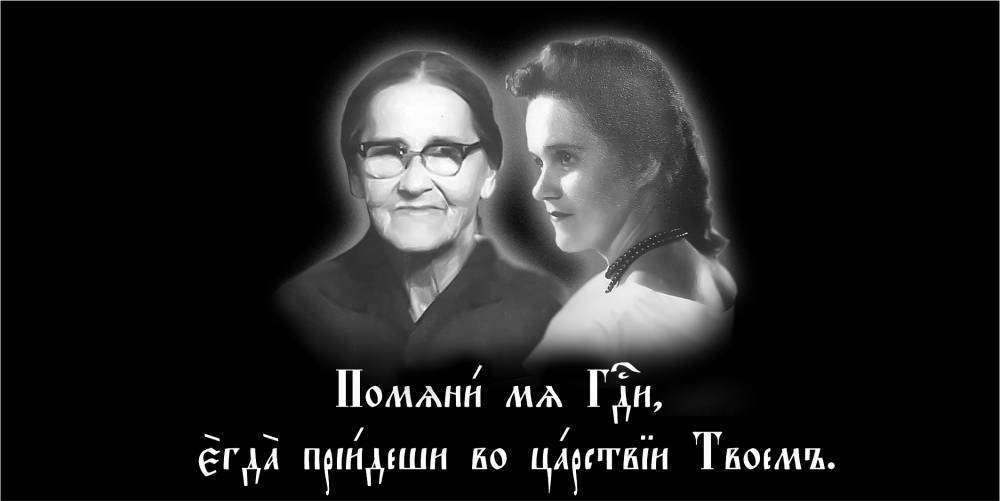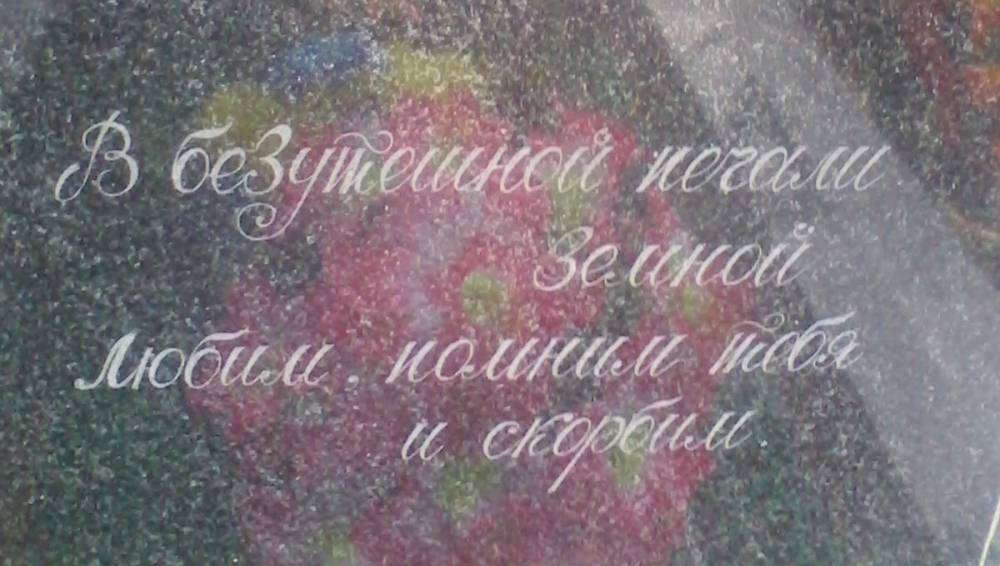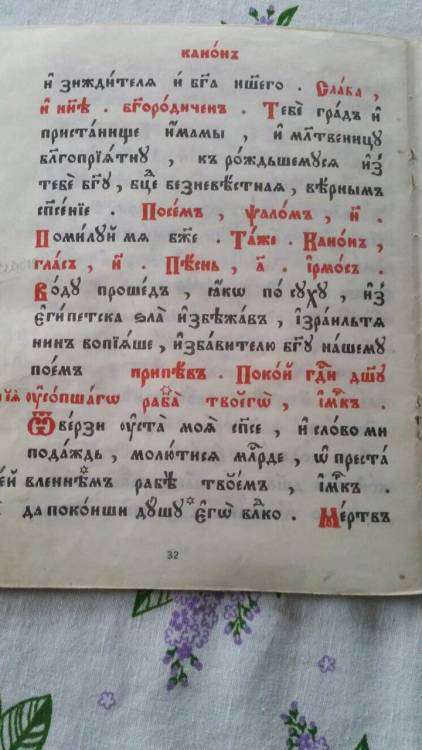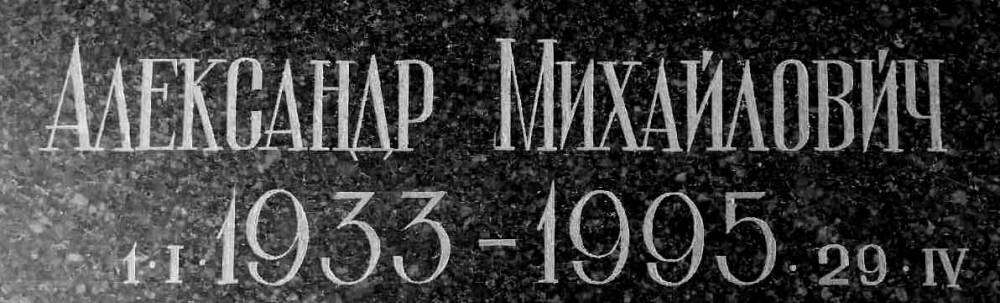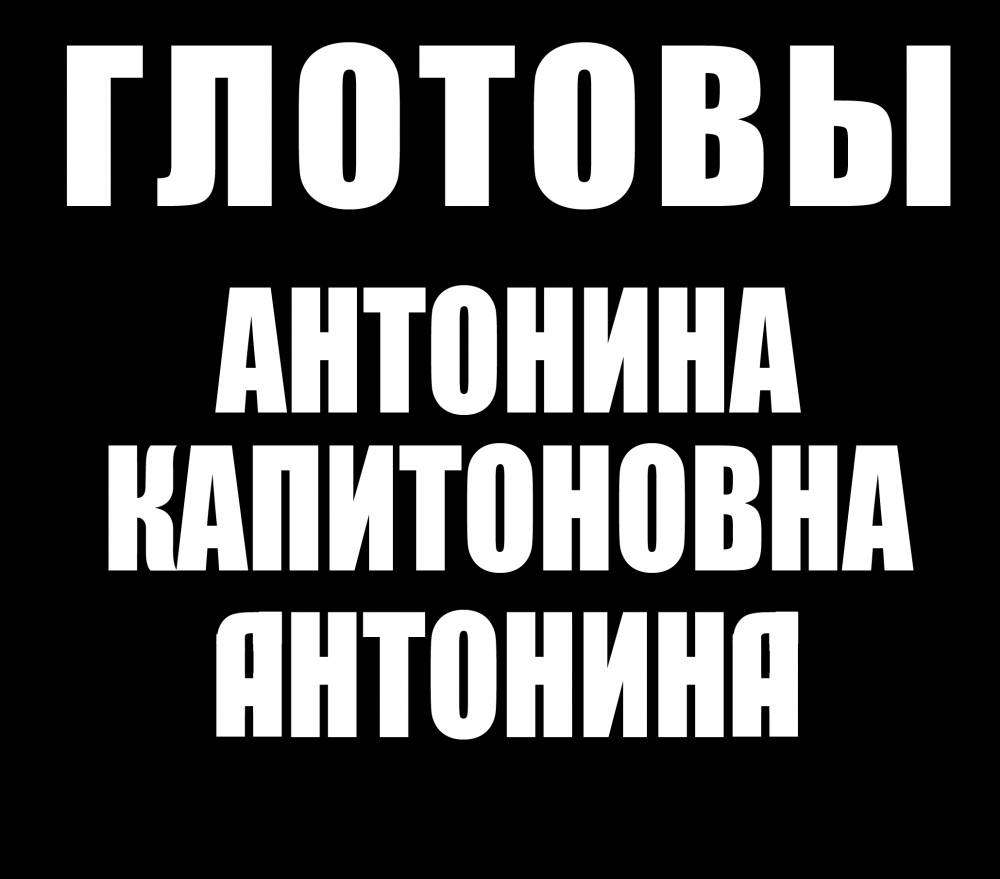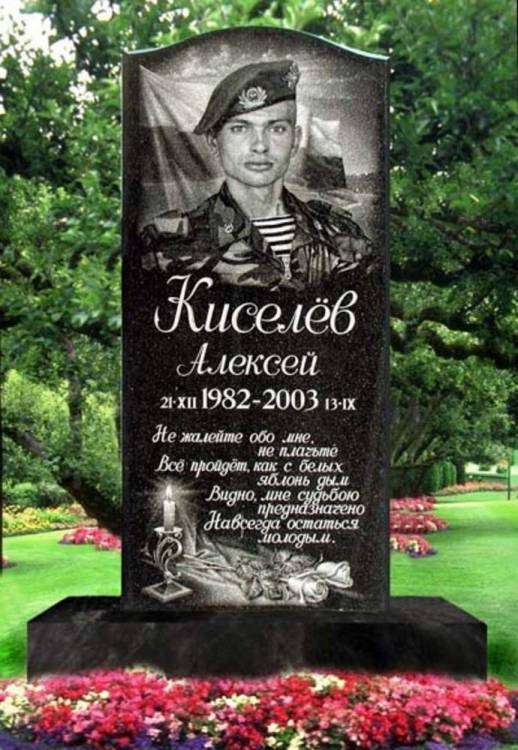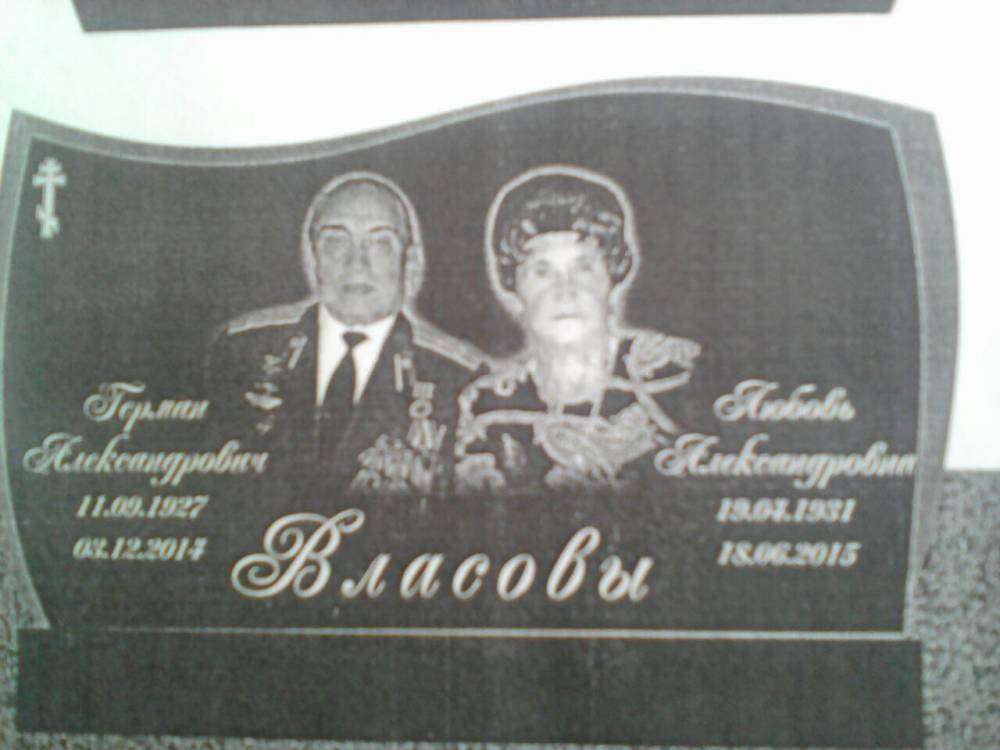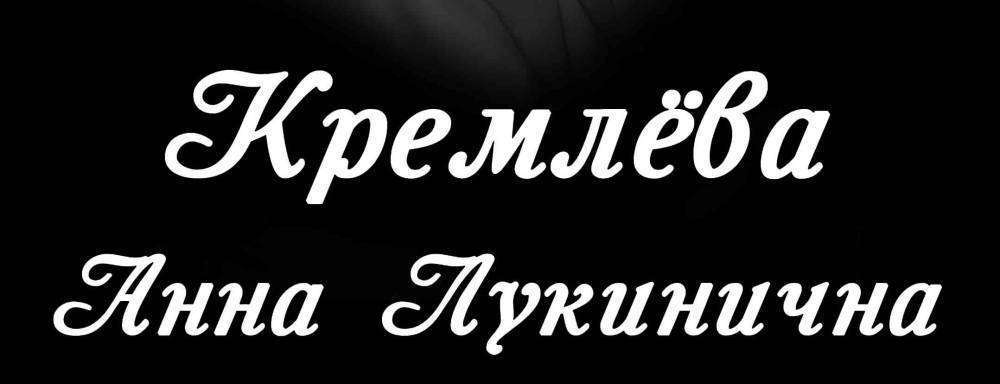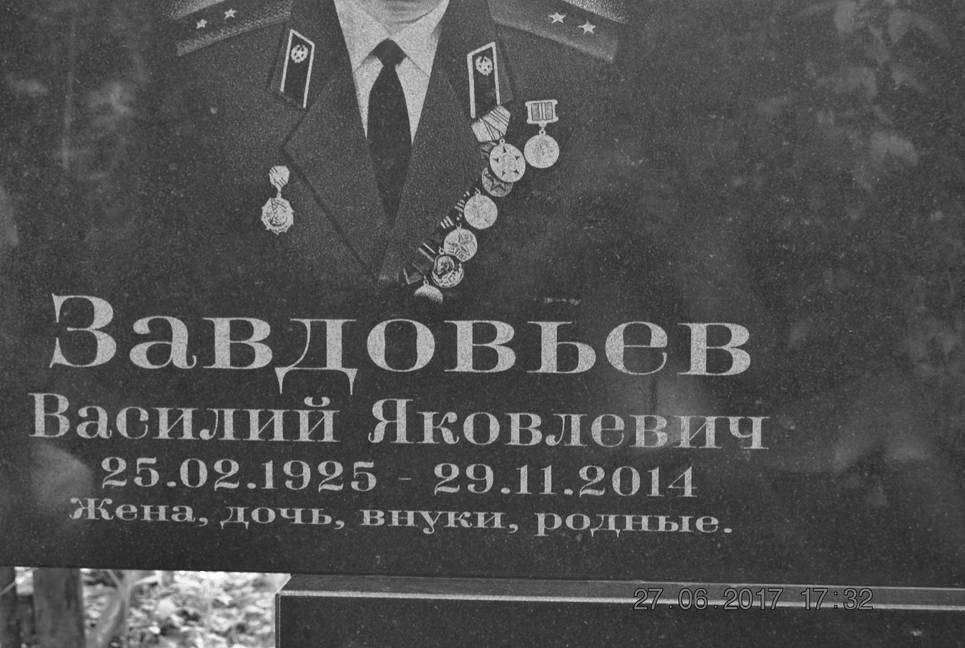
Помогите найти шрифт!
подскажите такой или очень похожий шрифт
Шрифт StaroUspenskaya ieUcs
Но не всё так просто. Надо делать таблицу соответствия, где какой "козюбрик" расположен на клавиатуре.
Проблема ещё в том, что в фотошопе этот шрифт отображается не корректно. Я делал через Ворд.
Получилось примерно вот так (это эскиз без ретуши фотографий, всё в хорошем качестве осталось на старой работе):
как называется шрифт кто знает? или похожий может есть
работа ручная, возможно, художник его вообще придумал)
Явно " художник " сам придумал, каряво и от руки. Возми пропись Нью Ромен. На много красивее будет.
Olietta script BoldItalic
Здравствуйте! Ребят, помогите со шрифтом пожалуйста. Не могу найти((( ПрИочень буду благодарна!!!)
Шрифт рукописный.
При сравнении одинаковых букв (е,с и др.) между собой просматриваются существенные различия в форме, размерах, наклоне букв и расположении их отдельных элементов, что характерно только для текста, написанного от руки.
Шрифт ручной, но может кто подскажет хоть что-то подходящее и похожее на это чудо.
Подскажите пожалуйста, какие шрифты использованы. Нечто близкое к Impact и Rubick.
Это ручной шрифт.
Поэтому и предложите заказчику тот же Impact. Там отличается по начертанию только буква А. Но это легко можно исправить, растрировав текст, и сделав гибрид букв Н и О, например.
Друзья, помогите найти данный шрифт. Очень похож на ArtScript, но буква С иная..
Помогите, пожалуйста определить шрифт, в инете выдает готика,но какой то не такой
Помогите определить какой шрифт, заранее спасибо
Похож на bickham script two, но блин он тонкий
Уважаемые, подскажите пожалуйста что за шрифт, переклинило, не могу вспомнить, хотя знаю что раньше часто его использовал.